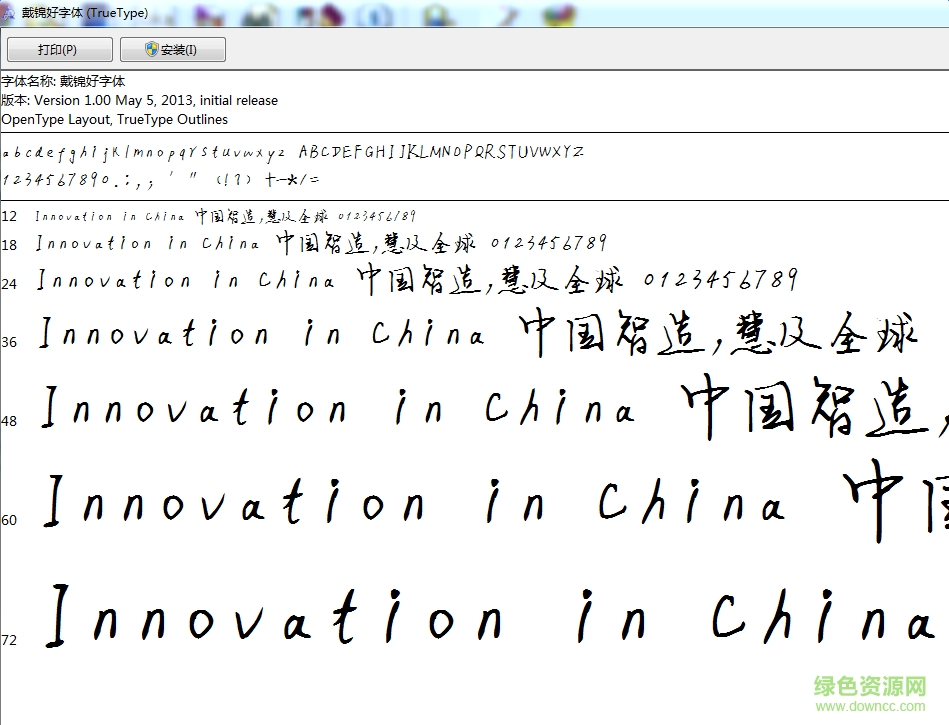
戴錦好字體是一款時(shí)尚酷炫風(fēng)格字體軟件,戴錦好體筆畫隨意灑脫,卻別有一番韻味,介于楷書與行書之間,創(chuàng)意獨(dú)特,深受廣大書法家喜愛(ài),還有更多好看字體歡迎來(lái)綠色資源網(wǎng)下載體驗(yàn)!
戴錦好字體是一款應(yīng)用于藝術(shù)設(shè)計(jì)方面的簡(jiǎn)體中文字體,該字體筆畫粗壯,尾部的甩尾有力且有豐富的筆觸細(xì)節(jié),大字效果突出且引人注目;并且最大程度還原作者書寫字形,細(xì)節(jié)表現(xiàn)完整,且字庫(kù)完整,可以廣泛應(yīng)用于名片設(shè)計(jì)、新聞媒體、宣傳海報(bào)、ppt、影視制作以及內(nèi)容用字等領(lǐng)域。